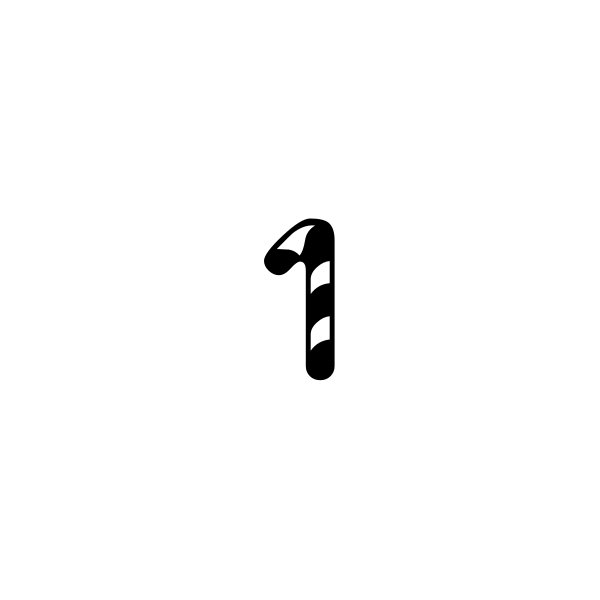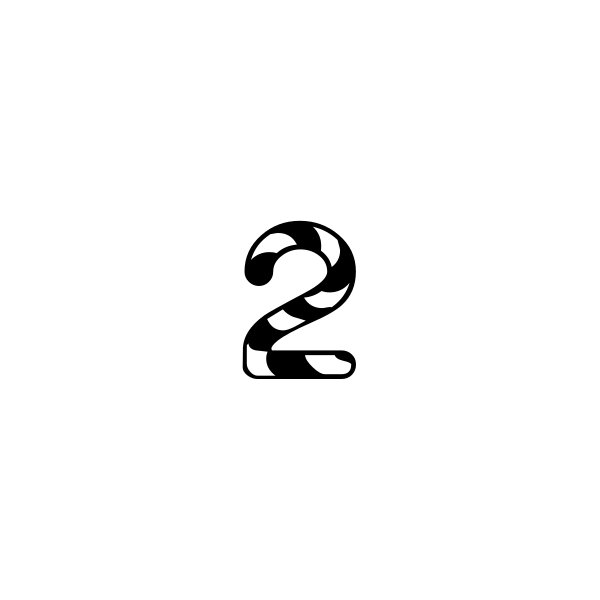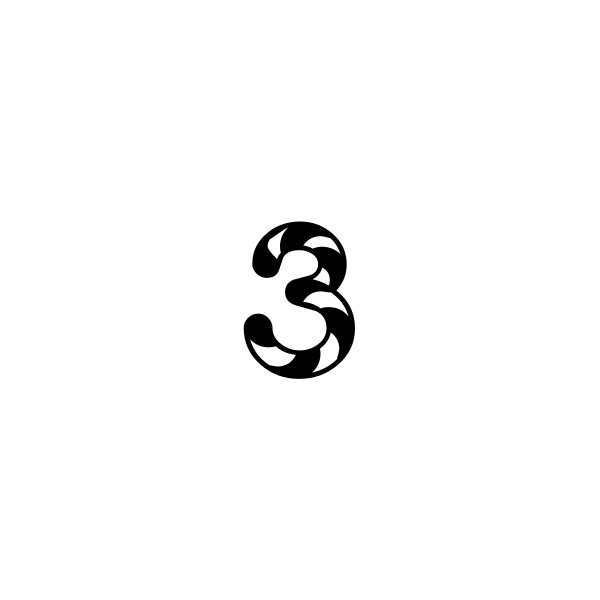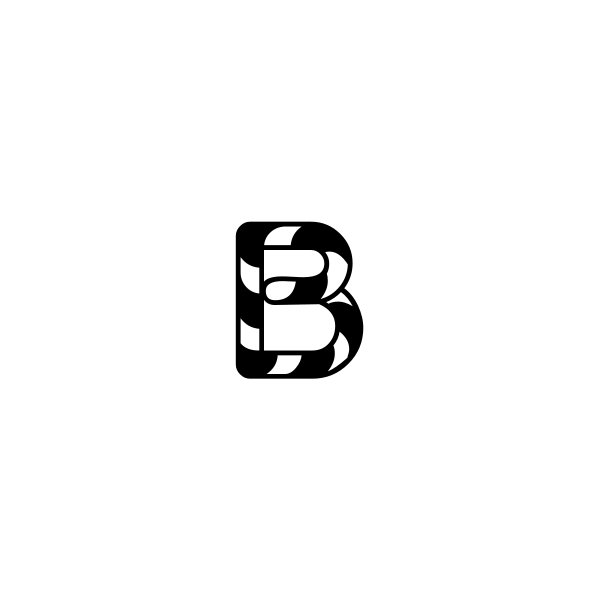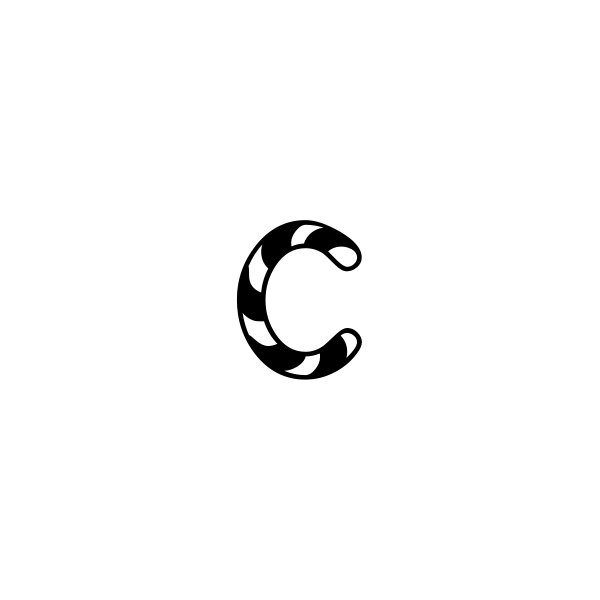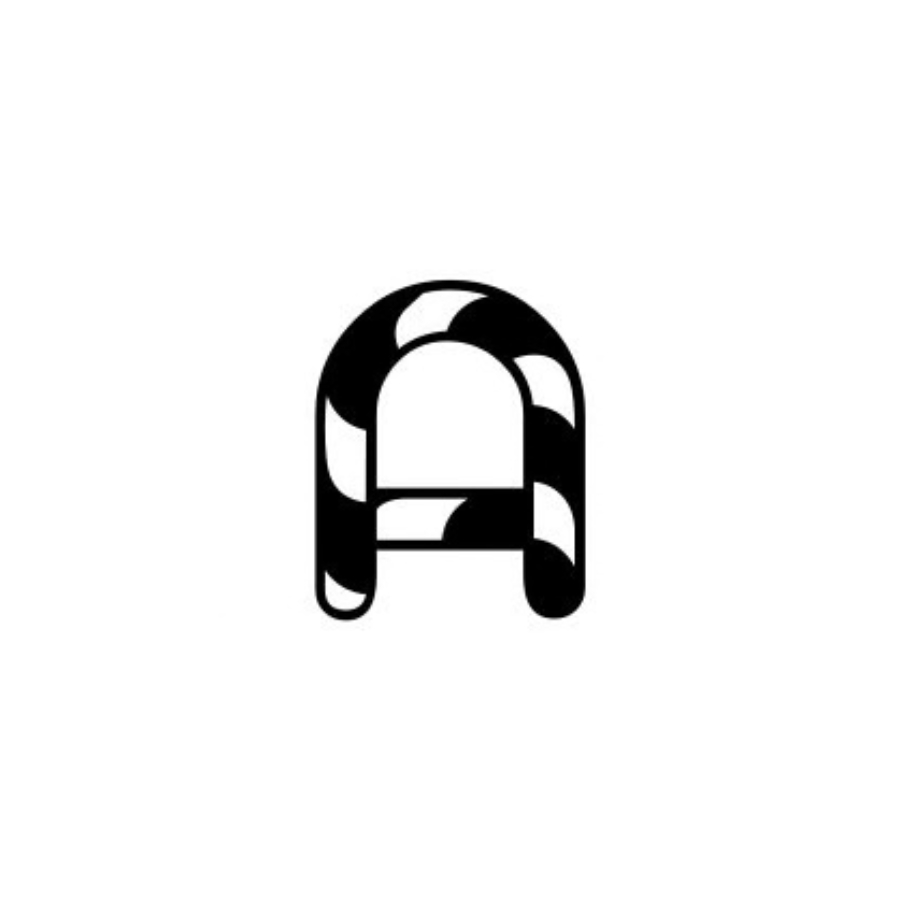
Candy Andy Monogramm Schriftart – Verspieltes Candy-Alphabet mit Grossbuchstaben, Kleinbuchstaben und Zahlen | Cricut-kompatibel
• Die Candy Andy Monogramm Schriftart ist ein verspieltes dekoratives Alphabet, inspiriert von den weichen Formen und der fröhlichen Optik von Süssigkeiten und Bonbons. Die Buchstaben besitzen runde Formen und dekorative Musterdetails, die dem Text ein lebendiges und kreatives Erscheinungsbild verleihen, während die Schrift gleichzeitig klar und gut lesbar bleibt.
• Die Schrift enthält einen vollständigen Zeichensatz mit Grossbuchstaben, Kleinbuchstaben und Zahlen von 0–9. Dadurch eignet sie sich ideal für Monogramm-Initialen, Namen und dekorative Schriftzüge.
• Der freundliche und leicht verspielte Stil macht diese Schrift besonders geeignet für Projekte, bei denen ein fröhliches und personalisiertes Design gewünscht ist. Die ausgewogenen Formen sorgen dafür, dass Texte gut lesbar bleiben und gleichzeitig eine dekorative Wirkung erhalten.
• Die Candy Andy Monogramm Schriftart eignet sich besonders gut für Monogramm-Designs, personalisierte Namen sowie dekorative Schriftzüge für kreative Bastelprojekte.